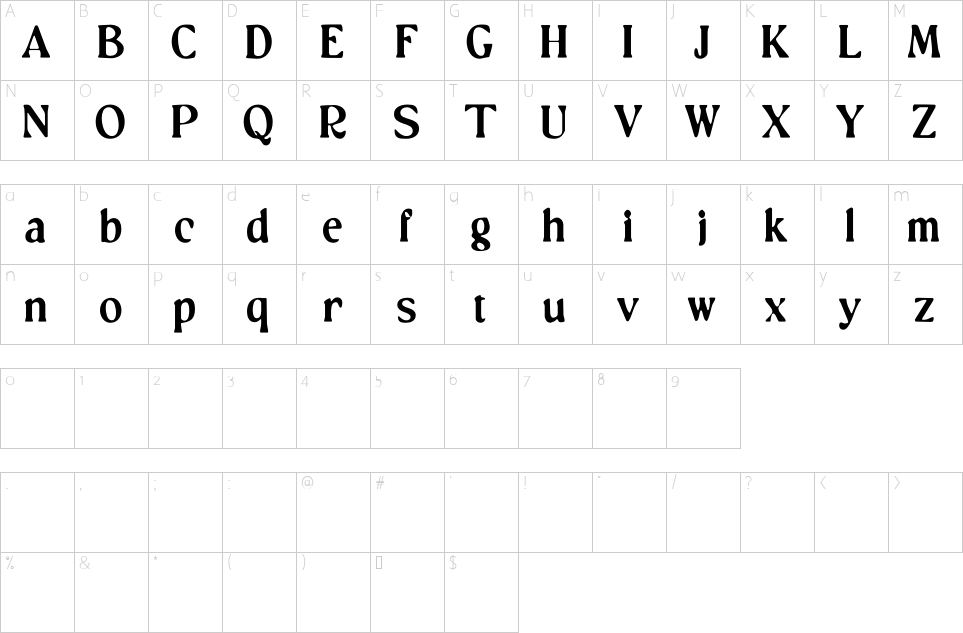
A fonte Marbley Blur é uma opção única e envolvente para o seu próximo projeto gráfico, oferecendo um estilo suave e elegante que se destacará entre as demais. Desenhada pelo Craft Supply Co, ela apresenta linhas curvas e texturas suaves, ideais para aplicar em nomes de empresas, nomes de usuários, e em qualquer outro tipo de texto que exija um toque de sofisticação. Com a sua baixa descarga de 173, a font é um item popular entre os designers, e a sua versão gratuita para o Windows e Mac torna-a ainda mais acessível. A Marbley Blur é uma escolha ótima para aqueles que desejam adicionar um toque de elegância e sofisticação sem comprometer a facilidade de uso. Teste-a agora e descubra por si mesmo o quanto ela pode transformar o seu trabalho de design.